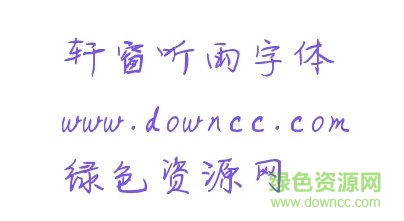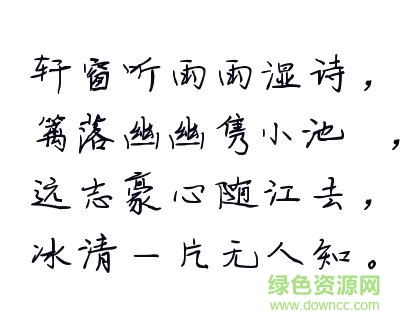
軒窗聽雨字體ttf
軒窗聽雨字體是一款很有意境美得藝術(shù)字體,字跡娟秀質(zhì)樸,給人干凈利落的閑適質(zhì)感,清晰濃厚的色彩讓人沉浸其中,如果你覺得不錯,就來綠色資源網(wǎng)體驗吧!
軒窗聽雨體字體特色
“軒窗夜聽雨,雨打芭蕉聲。輕問敲門人,疑是故人歸”
軒窗聽雨給人現(xiàn)世安好的寧靜之感,如靜靜夜晚凝聽雨滴落下的聲音,纏綿著屋外的芭蕉,而故人將至的不經(jīng)意和意外之喜,又使得字體生動起來,如果運用在廣告創(chuàng)意上,將有很大增益。
軒窗聽雨ttf